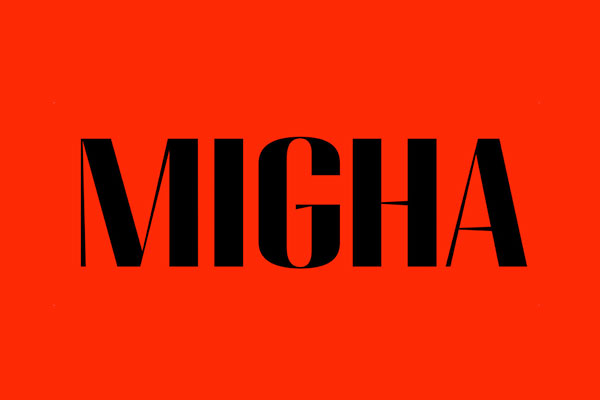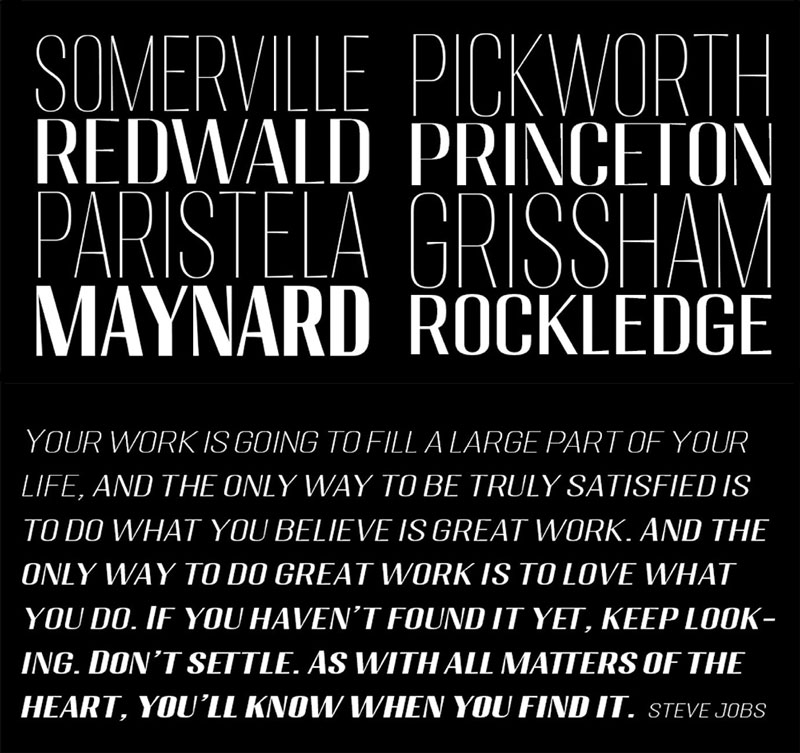
MIGHA字体
MIGHA是一款由Seniors Studio推出的免费英文字体,设计具有现代与复古感。这款字体非常适用于各类品牌、杂志、海报、徽标、标题和博客等。它具备一套完整的大写字母、数字、标点符号,并支持多语言。
值得一提的是,MIGHA字体家族涵盖了多种字重以及笔画粗细的调节,整个字体包竟然包含了惊人的96个字体文件,各种斜体、粗体、细体一应俱全。
MIGHA字体效果预览